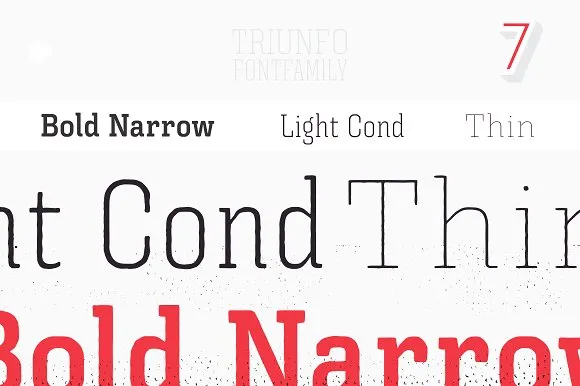
A fonte Triunfo é uma família serif desenvolvida pelo designer Hamilton, que se destaca por sua diversidade de pesos. Essa singular combinação oferece uma rica variedade que permite um uso único e inovador. O que torna Triunfo realmente especial são suas letras amplas variadas em largura, características exclusivas que a fazem não apenas singular, mas também única no mundo das fontes serif. Com diferentes níveis de peso que permitem uma gama completa de aplicações na tipografia, incluindo websites, revistas e livros, Triunfo aumenta a versatilidade do seu uso. É perfeita para designers profissionais ou iniciantes, oferecendo uma escolha de opções incríveis para criar visuais belos e eficazes em seus projetos.